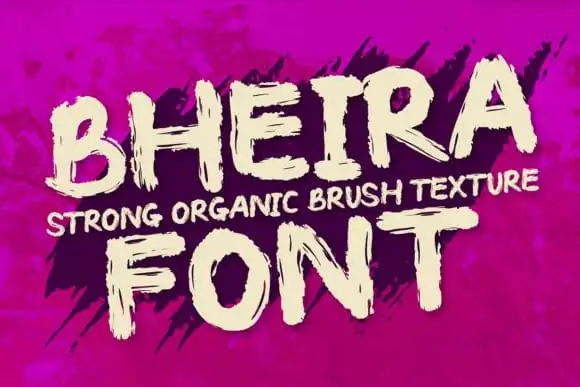
Bheira Brush Font – Download Grátis
A Bheira Brush Font é uma elegante escolha para eventos musicais e festivais, sua forma robusta e desbocada tornando-a ideal para destacar seu design no meio vibrante de um show ou evento musical. Desenvolvida pelo font designer Brithostype, essa é uma tipografia de display bold e robusta, criada com a ajuda de uma caneta-pen. Seu estilo atrevido e expressivo se assemelha aos adesivos de rock clássicos, mas na tela do computador. Adicione esta fonte às suas ideias criativas e observe como ela pode tornar seu design mais notável. Esta Bheira Brush Font é uma excelente opção para designers que procuram dar um toque especial a seus projetos musicais ou festivais de eventos, proporcionando aos leitores uma experiência visual vibrante e impactante.